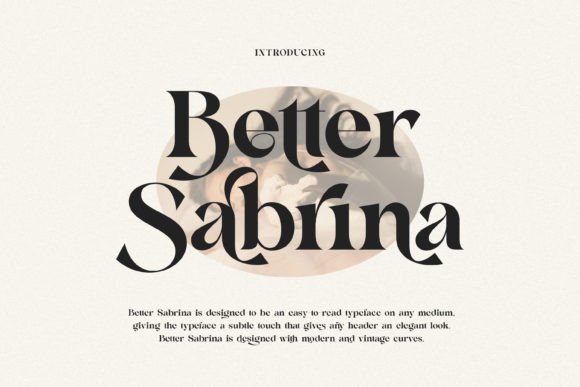
Better Sabrina
適切なデザイン要素を見つけるのは難しい場合がありますが、Better Sabrinaは作品を即座に引き立てる優れたコレクションを提供します。
POD(オンデマンド印刷)製品、結婚式の招待状、またはソーシャルメディアのグラフィックを作成している場合でも、Better Sabrinaは理想的です。